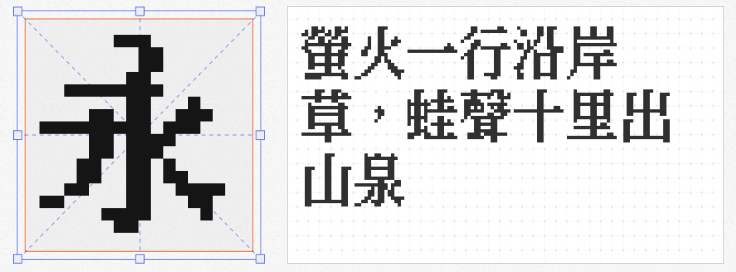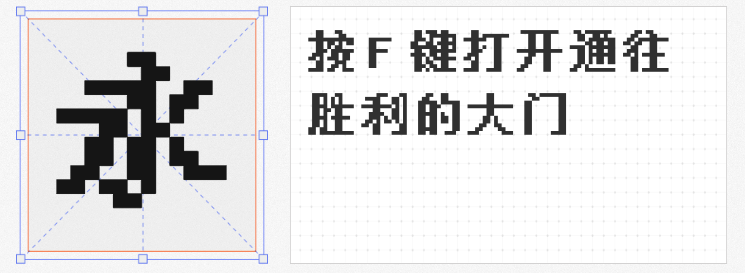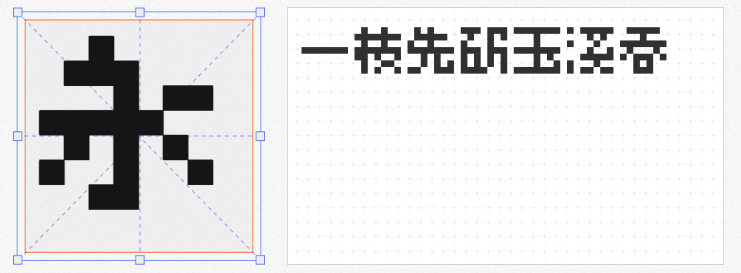
在复古游戏开发、像素风海报设计或怀旧主题的UI界面创作中,像素字体以其独特的颗粒感与机械美学成为视觉表达的核心元素。本文精选四款免费商用像素字体,涵盖不同字号、风格与文化适配性,助力设计师突破创意边界。
作为KHドットフォントシリーズ的衍生作品,长坂点宋16以16px点阵粗宋体为基础,针对繁体中文市场增补了Unicode基本区汉字、常用国字标准字体表及Big5常用汉字表,甚至融入日文IBM扩展字符。其设计团队精准捕捉到简体字市场已有类似风格的现状,优先完善繁体字库,未来计划扩展简体字符。这款字体用途多样,尤其在复古RPG游戏标题与怀旧招牌设计中,粗犷的笔画与规整的点阵结构形成强烈视觉冲击,成为传递东方文化韵味的利器。
由B站游戏爱好者DOUOA开发的甜橙点阵体,以7像素的超小字号实现清晰度突破。通过ZFONT修正字高与ROS信息后,其简体中文支持覆盖GB2312标准,笔画边缘锐利无粘连,在《甜橙点阵体》的实测中,即使在低分辨率屏幕下仍能保持可读性。这款字体凭借免费商用授权,成为独立游戏开发者与软件界面设计师的首选,尤其适合需要紧凑排版的像素风菜单或HUD元素。
基于文泉驿点阵中文字库的天王星像素(0.99版),以6763个GB/T 2312汉字及符号构建起完整的简体字库。其核心优势在于通过优化点阵算法,解决了传统粗体像素字笔画粘连的痛点,在《天王星像素》的对比测试中,即使放大至200%仍能保持字形独立。采用GNU GPL v2协议开源,允许自由修改与传播,但需注意商业使用需遵循协议条款,适合追求技术可控性的开源项目。
全小素以8px的超小字号挑战中文字符辨识极限,通过融合Galmuri、Chill点阵体等开源资源,实现简体中文GB2312与繁体BIG5的双标准覆盖,并支持日文、韩文。其设计团队在《全小素》开发日志中透露,通过精简笔画结构与动态权重调整,解决了小字号下汉字模糊的问题。这款采用OFL协议的字体,在复古芯片音乐海报与像素艺术展览中频繁亮相,成为跨文化设计的桥梁。
这四款字体不仅重新定义了像素字体的美学边界,更以免费商用的姿态推动设计民主化进程。无论是独立游戏开发者、UI设计师还是广告创意人,都能从中找到契合项目调性的视觉语言。